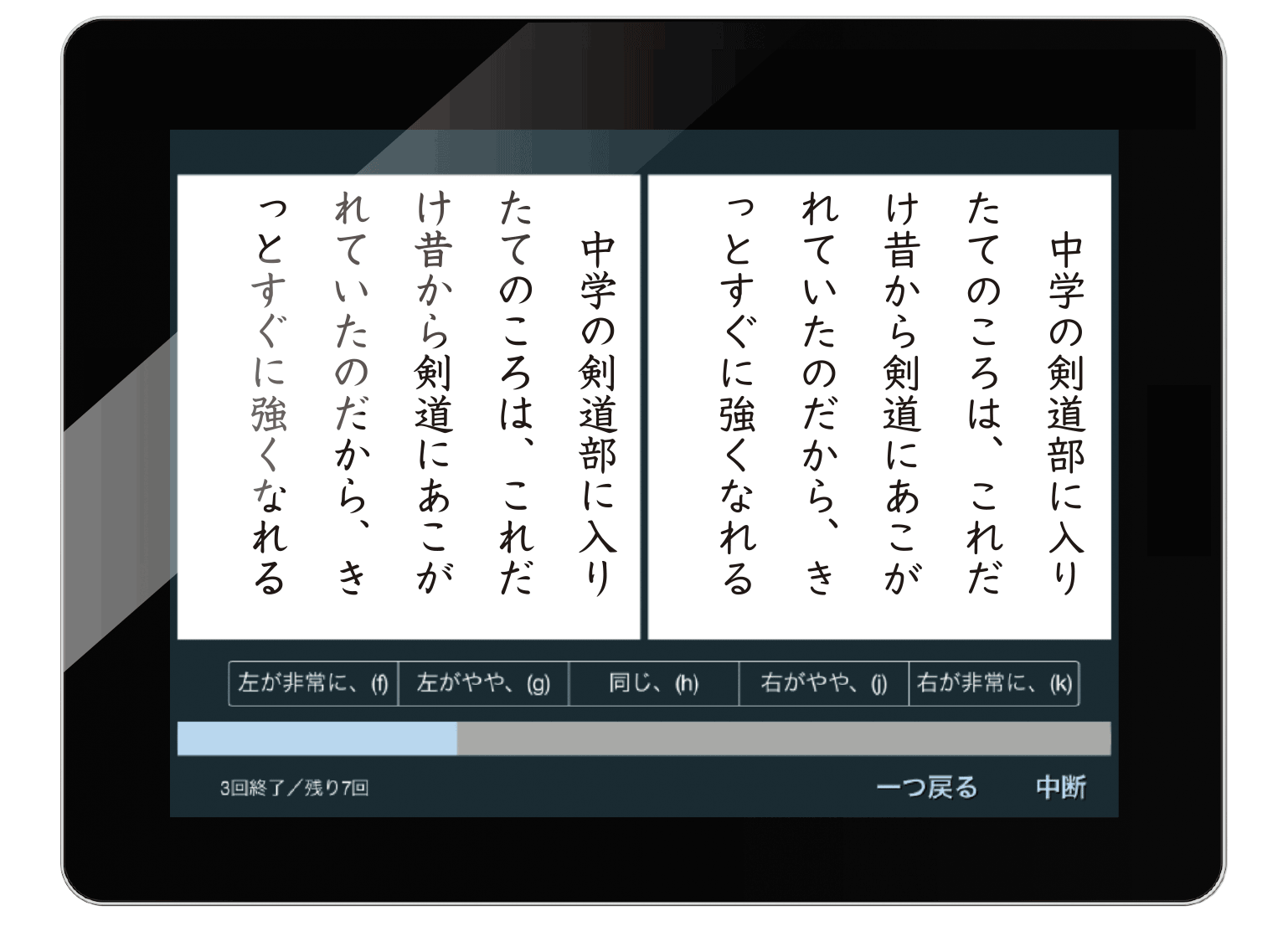
エビデンス(科学的根拠)
モリサワのUDフォントは
ユーザー評価に基づく読みやすさの
エビデンスを取得しています。
UDデジタル教科書体の調査結果
ロービジョン(弱視)
ロービジョン(弱視)者の見え方・見えにくさにはさまざまなものがあり、研究の第一人者 中野泰志教授による比較研究実験では、弱視の多様な見え方をシミュレートした実験に加え、弱視の高校生や成人、教員など200名以上を対象とした実験を実施しました。
その結果、比較した従来の教科書体よりも可読性に優れていることが実証されました。
慶應義塾大学 心理学教室 中野泰志教授
生徒や教員などからエビデンス(科学的根拠)を取得
UDフォント作成の経験豊富なデザイナーの判断に加えて、特別支援教育に携わる教員や拡大写本ボランティア等のヒアリングに基づいて、デザインの原案を作成し、ロービジョン(弱視)研究の第一人者 中野泰志教授によるユーザ評価に基づき、デザインをスパイラルアップしました。ユーザー評価では、多様な弱視の見え方をシミュレートした実験に始まり、弱視の高校生や成人、教員などに実験や調査を実施。延べ241人から得られたエビデンスを収集。ここではその中から2つの検証結果を紹介します。
1.デジタルデバイス(タブレット)での見やすさの検証
一対比較法で見やすさを尺度化
タブレットの画面に異なるフォントで作成した教科書体の一部を対提示し、どちらがどの程度、見やすいかを評定するシェッフェの一対比較法を用いて、見やすさの尺度を作成しました。15人の弱視者一人ひとりについて、国語と社会の教科書を用いて評価を行った結果、いずれの教科でも「UDデジタル教科書体」が最も見やすい書体であることがわかりました。 なお、ぼやけて見えにくい、まぶしくて見えにくいという弱視者のさまざまな見え方を人工的にシミュレートにする方法を用いて、さまざまな条件で見やすさを検証する実験も実施しました。その結果でも「UDデジタル教科書体」が最も見やすい書体であることがわかりました。特に、まぶしさを感じている弱視者にとって効果的であることがわかりました。
一対比較法を用いた評価画面(縦書き:国語)
教科別の教科書の見やすさの尺度(弱視成人全体の結果)
*数値が大きいほど見やすいことを示す
2.紙に印刷した際の見やすさに関する弱視児や視覚支援学校の教員に対する調査
弱視教育に携わっている教員・専門家65人へのアンケート調査、全国の視覚支援学校に在籍している弱視の高校生42人に対するヒアリング・アンケート調査、全国の視覚支援学校で弱視生徒を担当している教員104人に対するアンケート調査を実施しました。4種類の教科書体で作成した国語と社会のサンプル教科書を見比べ、読書に適しているかどうか順位付けをしてもらった結果、弱視生徒にとっても教員から見ても「弱視児童生徒の読書に最も適した教科書体」は「UDデジタル教科書体」であることがわかりました。
「読書」の際の見やすさ度合い(最高値を100とした比率)
ヒアリング・アンケートに協力した弱視生徒の視力分布
ヒアリングに協力した弱視生徒は、白内障(7人)、黄斑変性症(2人)、網膜色素変性症(2人)、未熟児網膜症(5人)、視神経委縮(4人)などの眼疾患を含む。
ディスレクシア(読み書き障害)
大阪医科大学LDセンター奥村智人氏の研究において、読み書きに困難さがある26人の小学2~6年生を対象に、UDデジタル教科書体を含む4つの教科書体で縦組みと横組みの文章を制作し、一対比較法を用いた主観的読みやすさに関する検討が行われました。
分析の結果、縦横組みともに「UDデジタル教科書体」が、最も読みやすい書体として子ども達に選択されました。(日本眼鏡学会「眼鏡学ジャーナル 第21巻 第2号」に掲載)
大阪医科大学LDセンター奥村智人氏
BIZ UD新ゴ・BIZ UD新丸ゴ・BIZ UD黎ミンについて
BIZ UD新ゴ・BIZ UD新丸ゴ・BIZ UD黎ミンは、慶應義塾大学と共同で行った比較研究でその優位性が検証されたモリサワUDフォントをベースに作成されています。「必ず伝えたい情報」「注意を促したい文言」「さりげなく添えたい文章」など、必要な表現に合わせてフォントを変えることが可能となり、情報の「伝わりやすさ」に大きな差がつきます。数字の多い文書や提案資料、公的文書、各種案内など、より多くの人が目にする文書の作成に最適です。
BIZ UDフォントの調査結果
従来のビジネスフォントの比較調査
監修:大阪医科大学 LDセンター 奥村智人 氏・中西誠 氏
全国93カ所の「ハロー!パソコン教室」を対象に、UD書体の比較調査を実施。BIZ UDフォントと標準的なフォントの「読みやすさ」を検証しました。
さまざまな年代の方にとっても、「BIZ UDゴシック」、「BIZ UD明朝」ともに標準的な書体より読みやすい書体として選択されました。
回答者:10代~80代の1603名
※モリサワUD書体は、すべてUD書体のエビデンスを取得していますが、TrueTypeフォント化にあたり、一部デザインを調整しています。